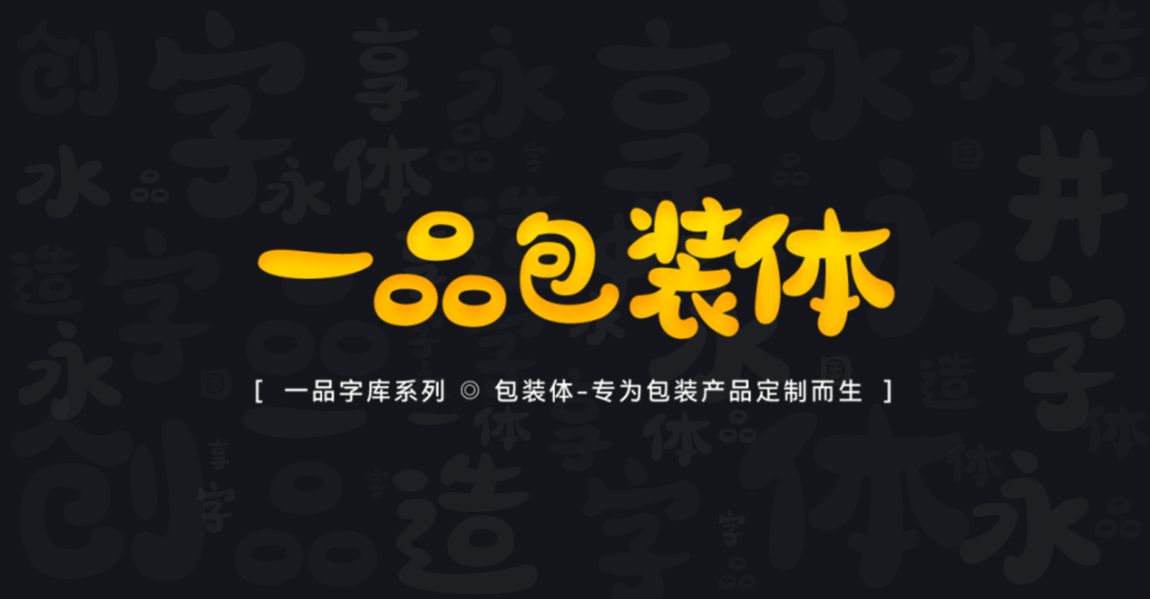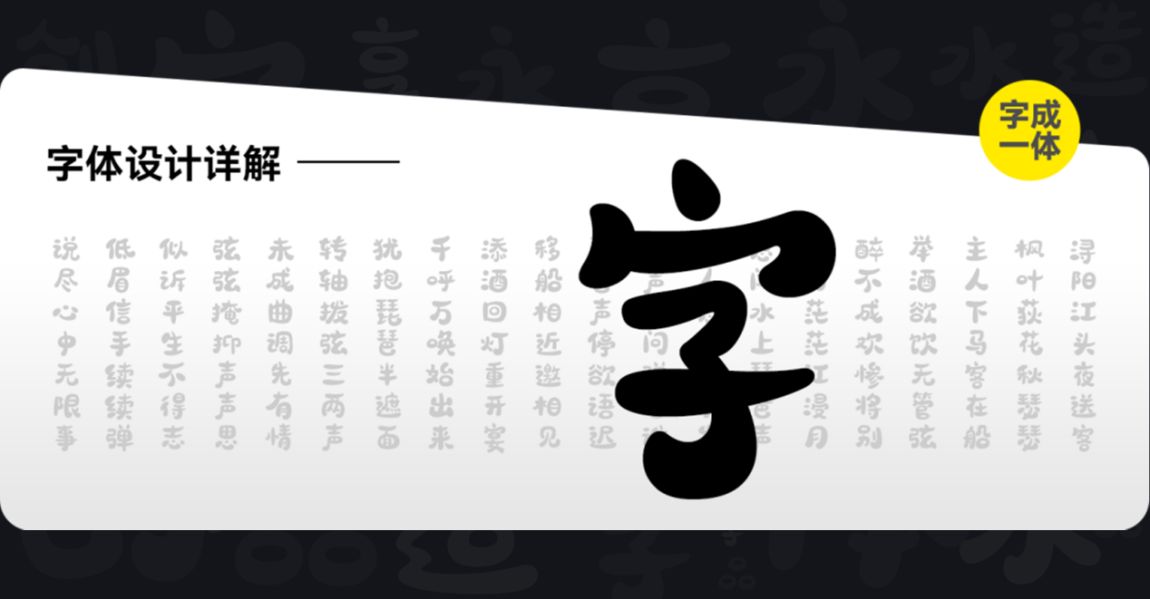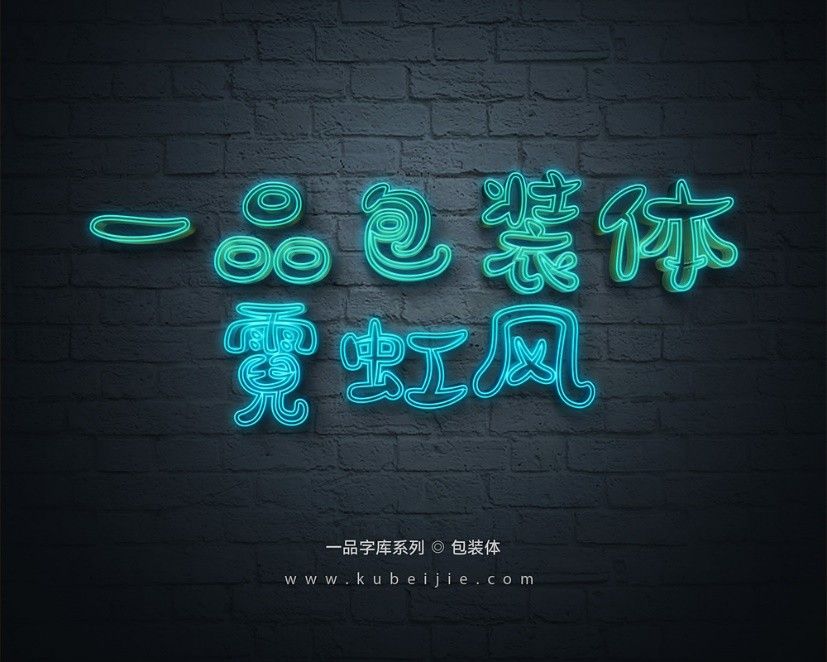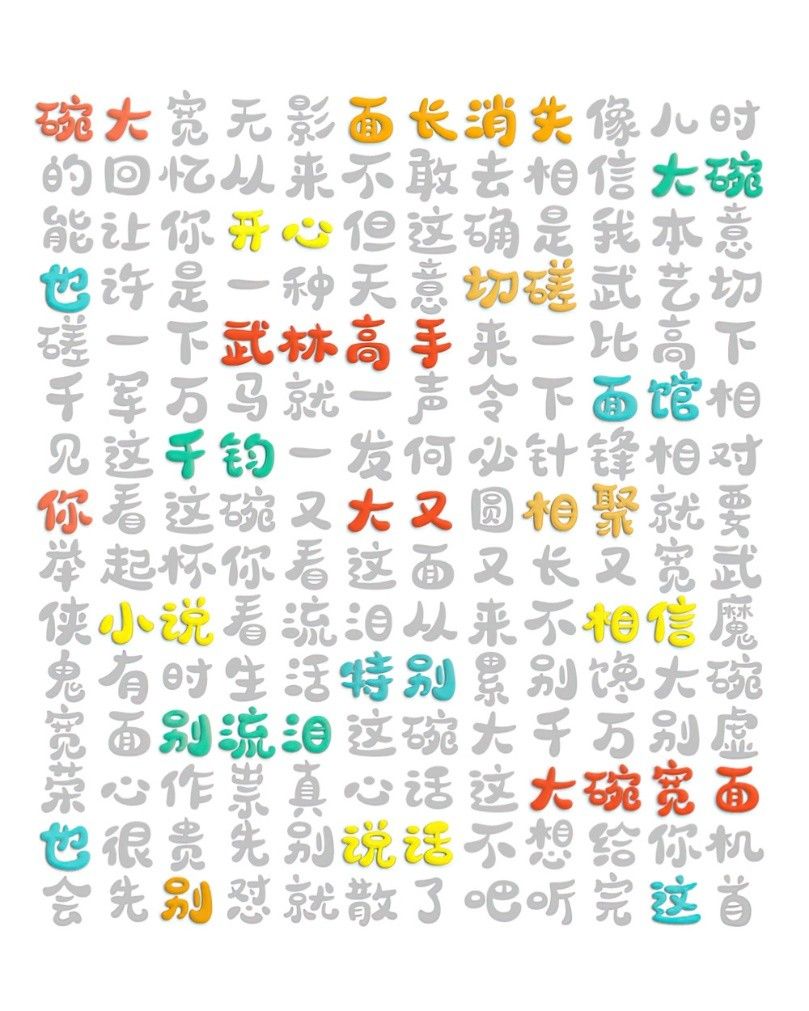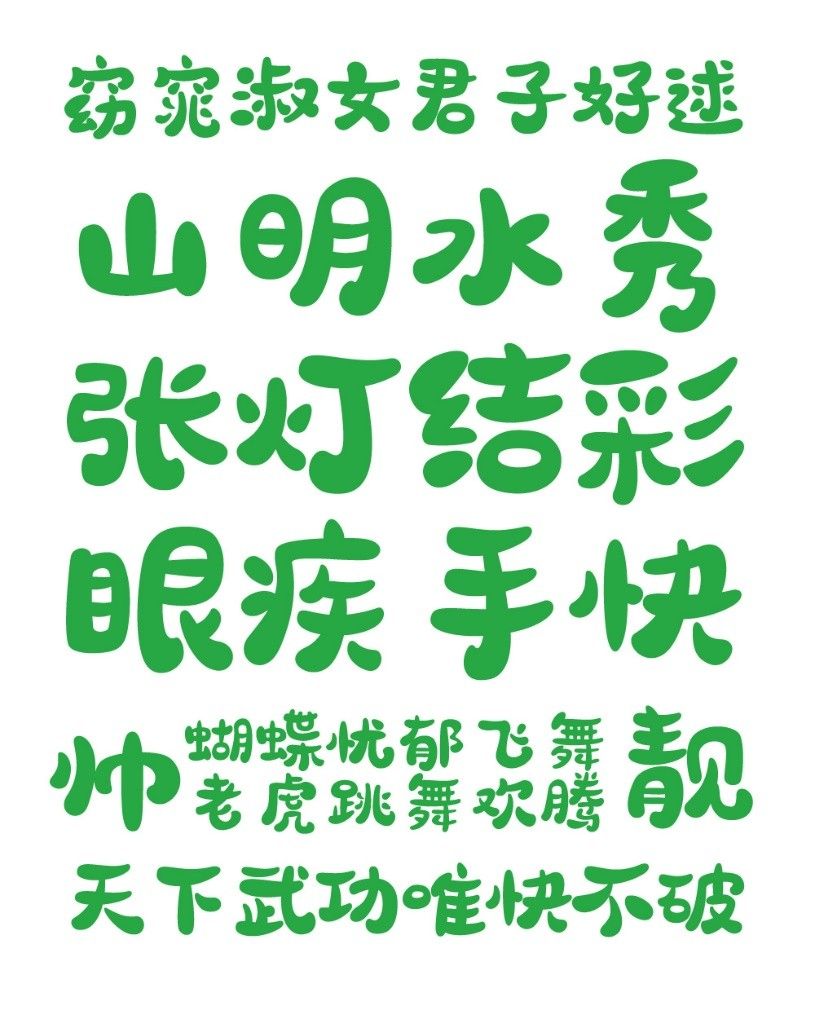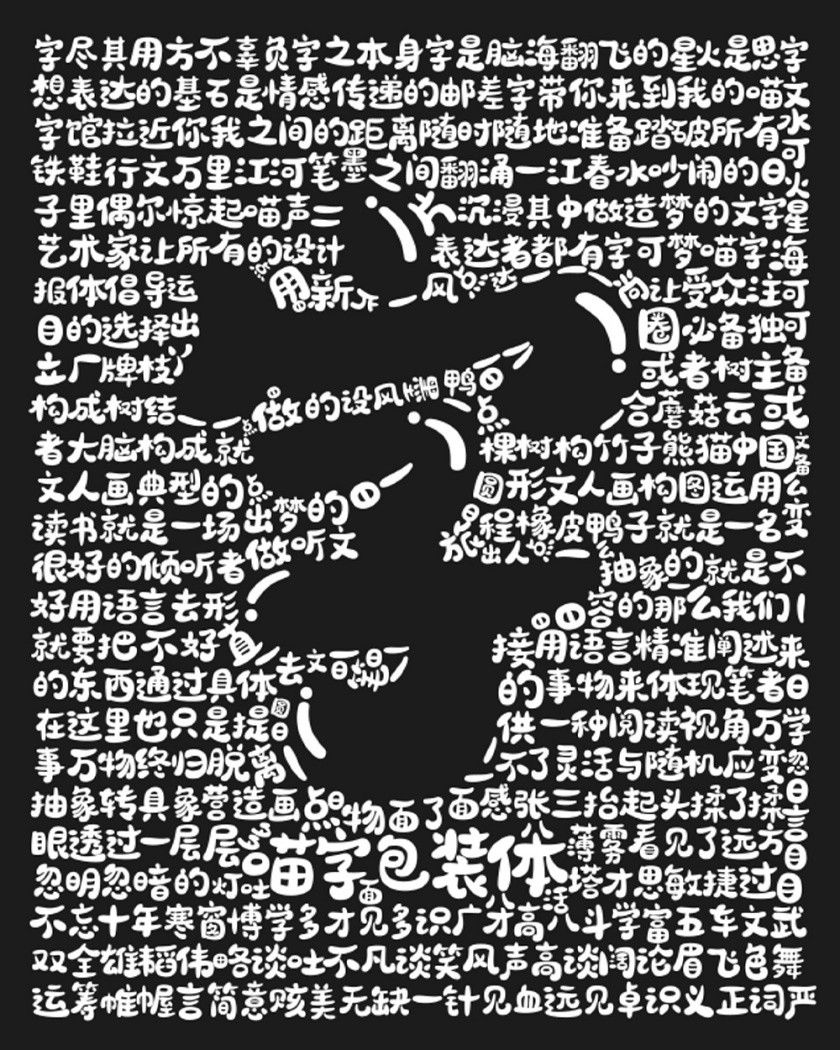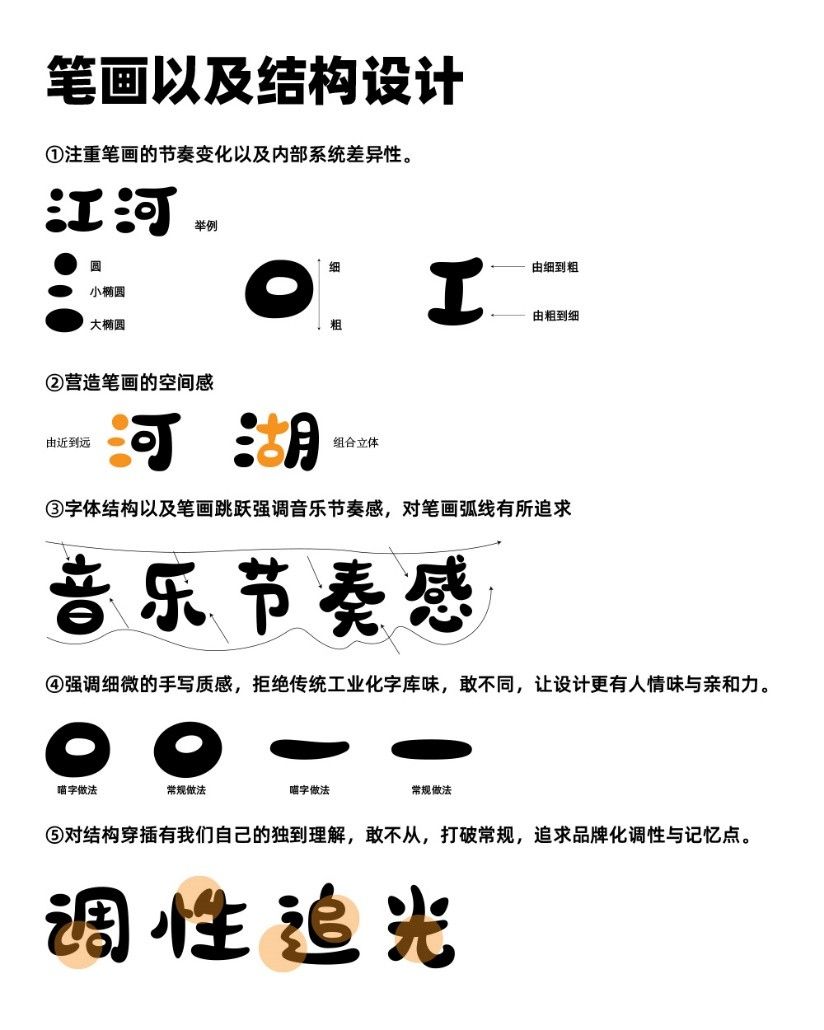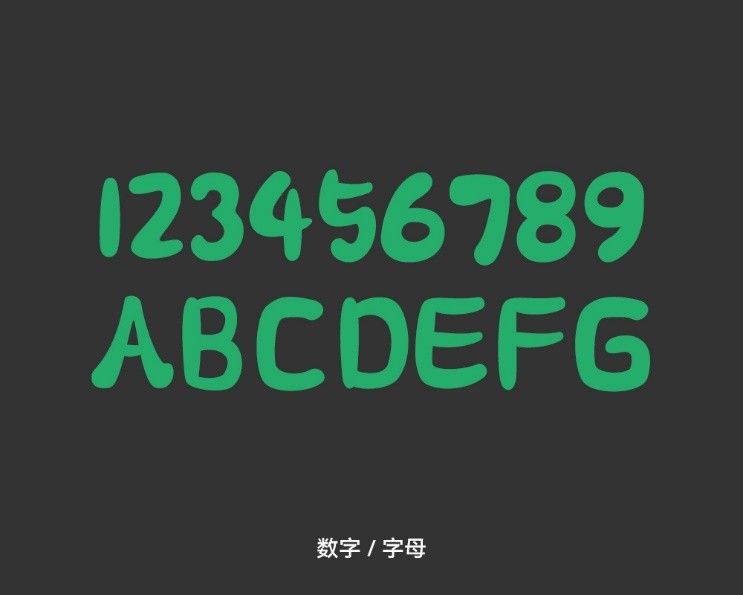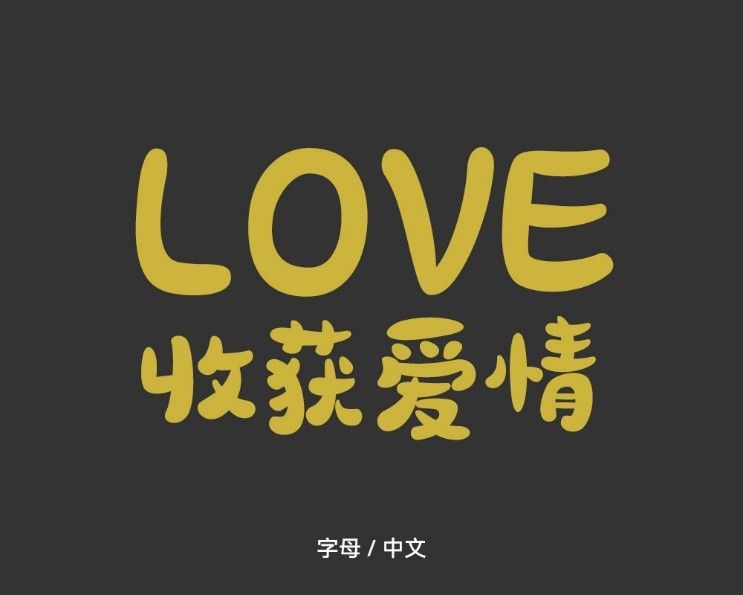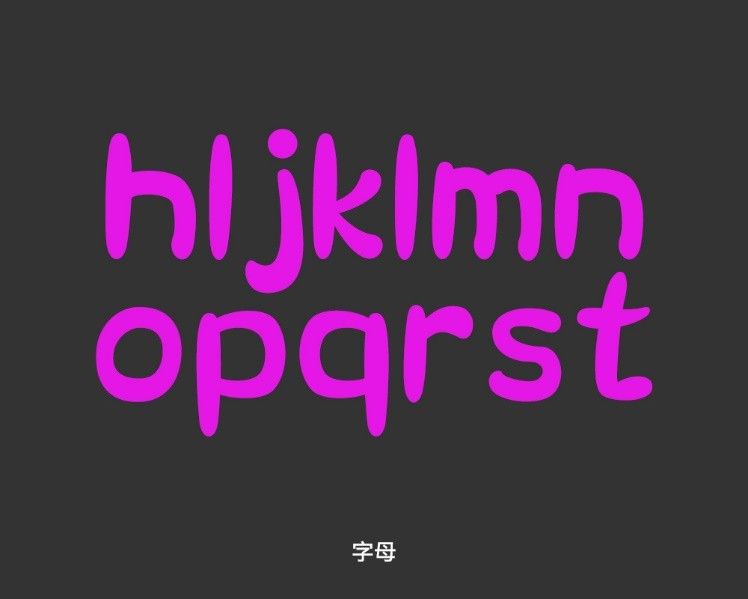
就连一品威客都曾遭受过类似的“惨案”,给品牌传播带来过不小的影响,事件虽然过去已久,但一品威客始终将此事件铭记于心,故于2021年8月1日起,一品威客就携手旗下酷贝街正式开启百人造字公益计划,立志要做出一款所有人都能免费学习使用的公益字体。
随着造字计划的进行,酷贝街打造的“一品字库”也随之上线多款字体供广大网友使用。而为了照顾到广大网友,一品字库于8月27日正式上线“一品包装体”供所有人免费学习使用!是的,你没听错是免费学习使用。
因为此套字体创作灵感来自于行书书法走势,设计团队取其部分精髓并结合当代设计师手法创作而成,专为包装行业而设计。为此,字体的设计风格“活泼、跳跃、手绘、圆润、可爱、灵动”,排版风格打破以往传统手法,注重灵活机动性。
正如名字所示“包装体”,首推的运用场景便是快消品包装上,其次是作为标题运用。当然并不限制多方位运用,海报、标志、横幅、等均可。
一品包装体以国标GB2321-80为基准,涵盖了6763个简体中文汉字、数字和英文字母。
一品包装体字体详解
字体效果详情展示